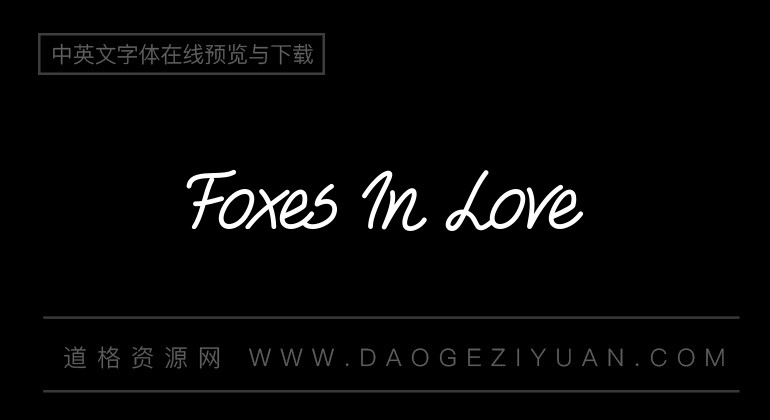
? Foxes In Love 字体是一款让人感到温馨的草书字体。它的字形简单,笔画圆润,每一个字母都有着柔和的曲线,可以轻松地融入到任何设计中。它的笔触轻柔,充满着浪漫的气息,是一款非常适合用于浪漫的婚礼、纪念日卡片、婚礼邀请函等等的字体。内容介绍
Foxes In Love是一款非常不错的手写艺术字体,具有很好的视觉感,适合于文化类的宣传设计、商业类品牌的广告和产品包装设计以及个性化文字排版等较多场景。